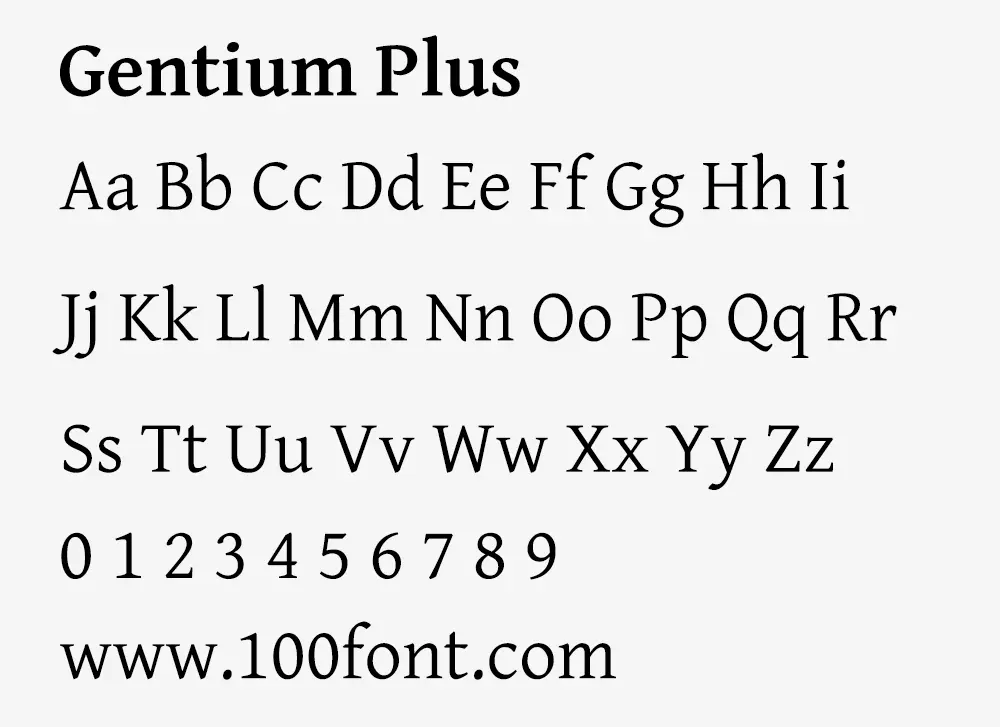
Gentium是一種開源字體,由美國設計師Victor Gaultney創造,它的目的是為了提供一個易於閱讀和具有國際性的字體,適用於各種語言和字符集。Gentium擁有廣泛的Unicode支持,包括拉丁字母、基本和擴展的希臘字母、西裡爾字母、亞美尼亞字母、格魯吉亞字母和其他Unicode字符,這使得Gentium成為多語言文本的理想字體選擇。
Gentium的設計簡潔明快,字母形狀和線條平滑,易於閱讀。因此,它已成為許多學術出版物和在線文檔中廣泛使用的字體之一,也是許多開源軟件和操作系統的默認字體之一。
Gentium Plus基於原始的Gentium設計,但擴展了字符和字形,並且幾乎完全支持拉丁語,西里爾文和希臘語。
Gentium Plus經過精心設計,可支持三種字體的全系列字體,同時為其設計帶來和諧。每種字體包含 4200 多個字形,並支持對多語言文本有用的高級 OpenType 功能,包括仔細的音調符號定位和小寫字母。
拉丁文和西裡爾字母用於書寫世界各地的數千種語言。Gentium Plus為這些書寫系統提供全面的支持,幷包括對語言學和識字工作有用的各種附加字符和符號。Gentium Plus還支持希臘文字。